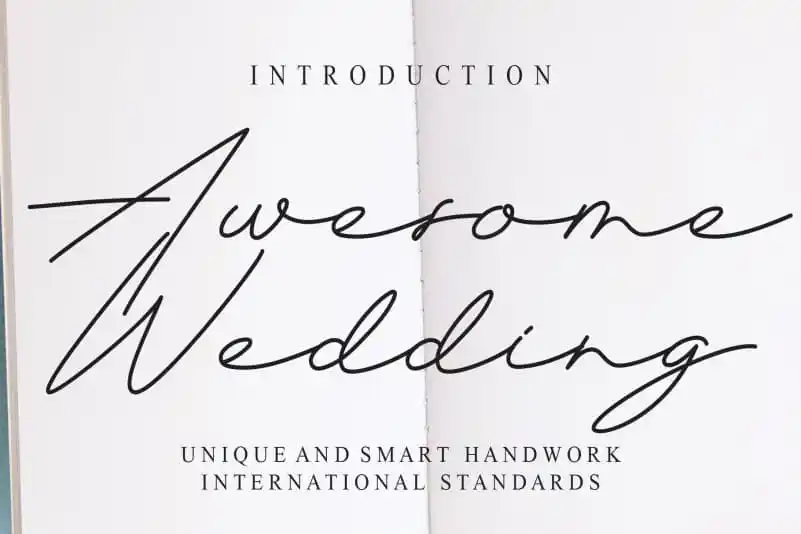
Awesome Wedding Handwritten Font – Fonte Grátis
Awesome Wedding Handwritten Font
Descubra uma fonte para sua próxima celebração especial com a “Awesome Wedding Handwritten Font”. Esta elegante e romântica fonte escrita à mão foi criada por um designer talentoso chamado creativeletter. Ela irá dar seu evento de casamento ou qualquer outro aniversário ou ocasião especial uma sensação única e memorável. Não é apenas uma escolha de texto, mas uma experiência imersiva que você pode personalizar para destacar cada detalhe do seu evento. Seja em um cháchara casual ou um casamento de sonho, essa fonte irá transformar suas palavras em uma obra-prima visual. Seja por sua facilidade de uso ou a beleza única da forma e dos traços, a Awesome Wedding Handwritten Font é perfeita para quem busca algo especial para seus momentos mais importantes. Se você está planejando um grande evento, essa fonte oferece uma maneira criativa de expressar o seu amor pelo casamento. Abrace cada detalhe do seu dia com um toque autêntico e sofisticado que apenas esta fonte pode proporcionar.